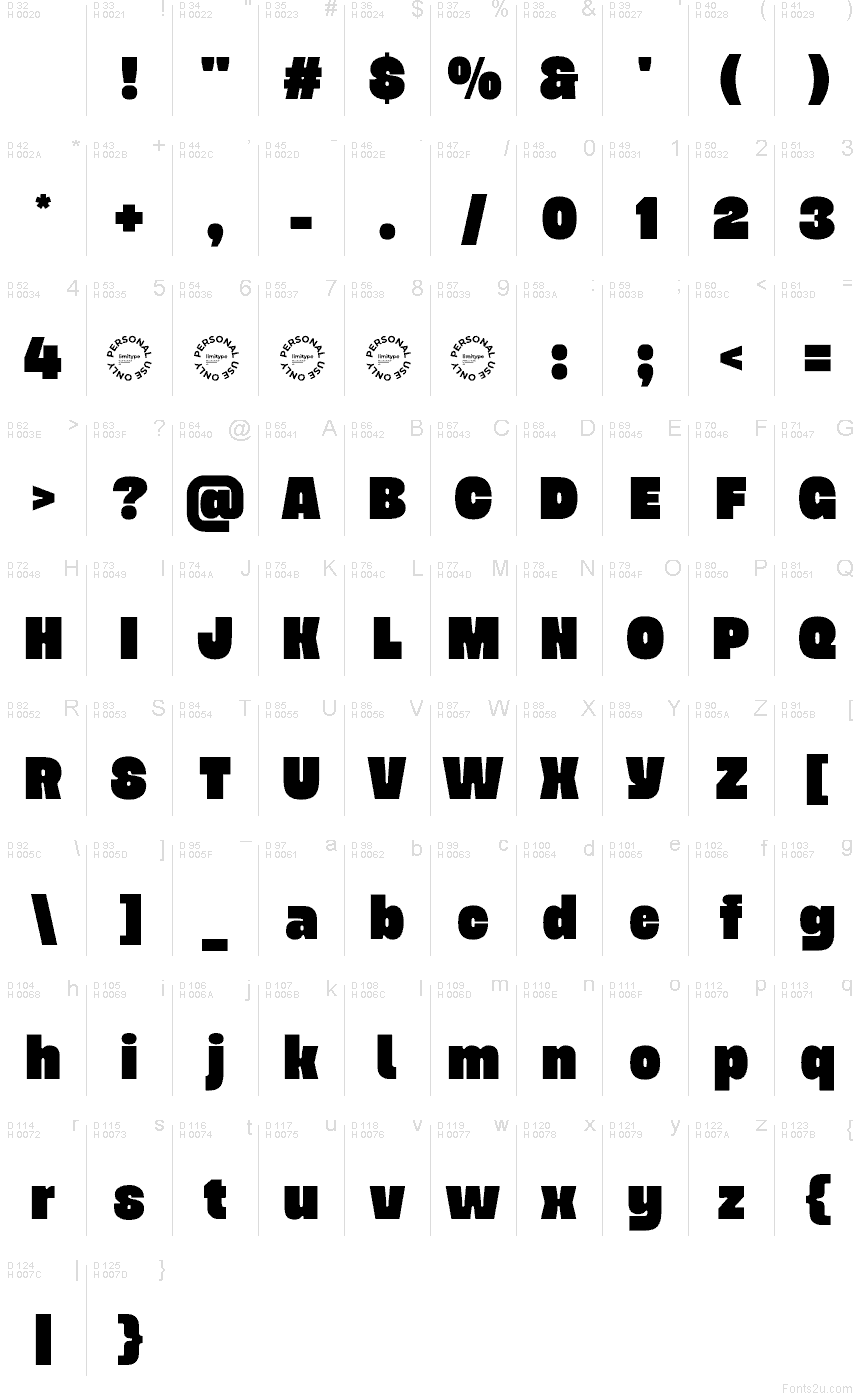
Oresta Bold de Limitype es una tipografía sans serif gruesa y gratuita con una silueta sobredimensionada y muy compacta. Sus trazos anchos, curvas exteriores suaves y pequeños cortes redondeados aportan a las letras un aspecto denso y dinámico. Posee la fuerza visual de una tipografía de cartel recortada a mano.
El llamativo lenguaje visual de las promociones deportivas y el streetwear se adapta a carteles de eventos, señalización de estadios, artículos promocionales de equipos y envases de alimentos impactantes. Su mayor fortaleza son los titulares de carteles, donde las letras anchas convierten unas pocas palabras en una masa gráfica sólida con la contundencia de un logotipo.